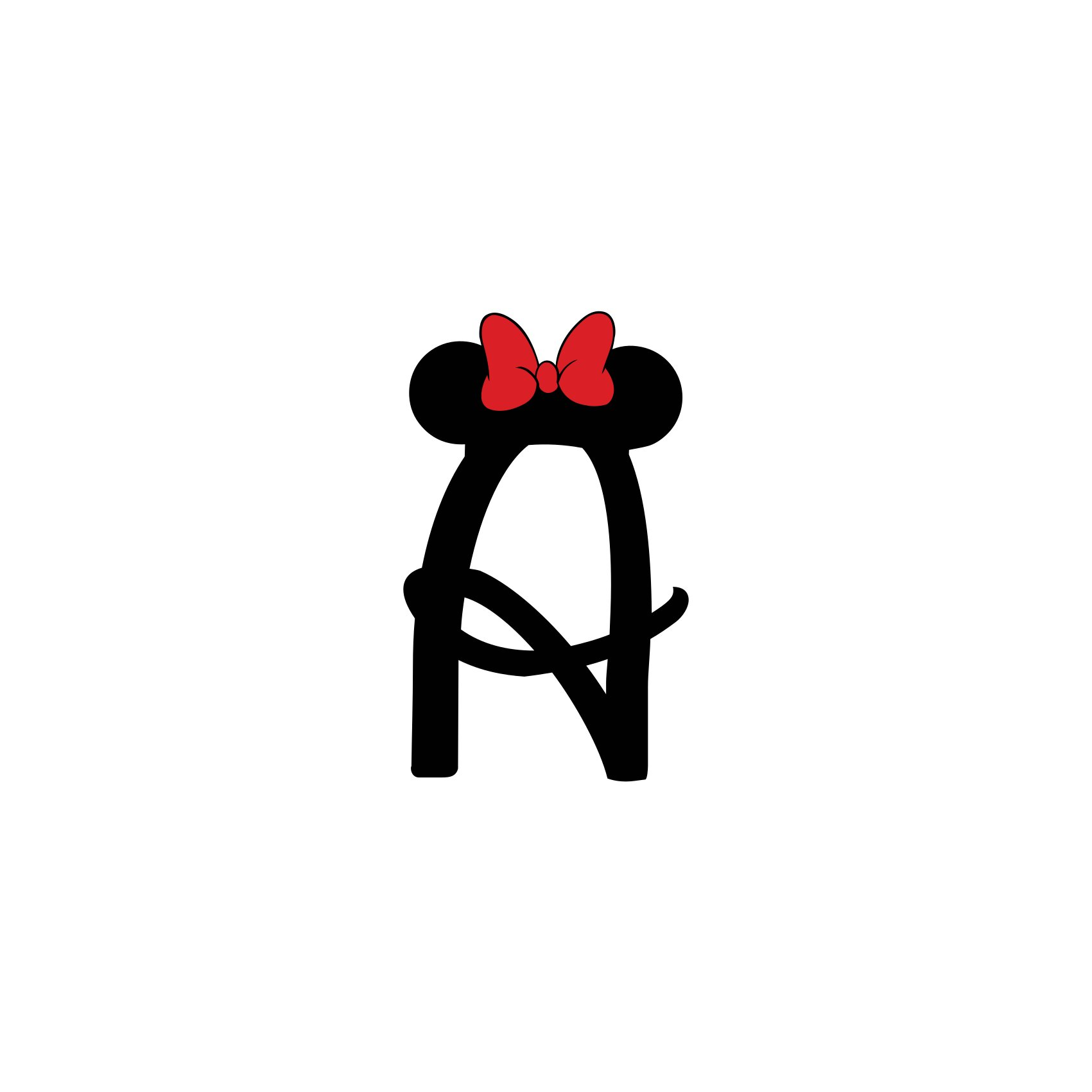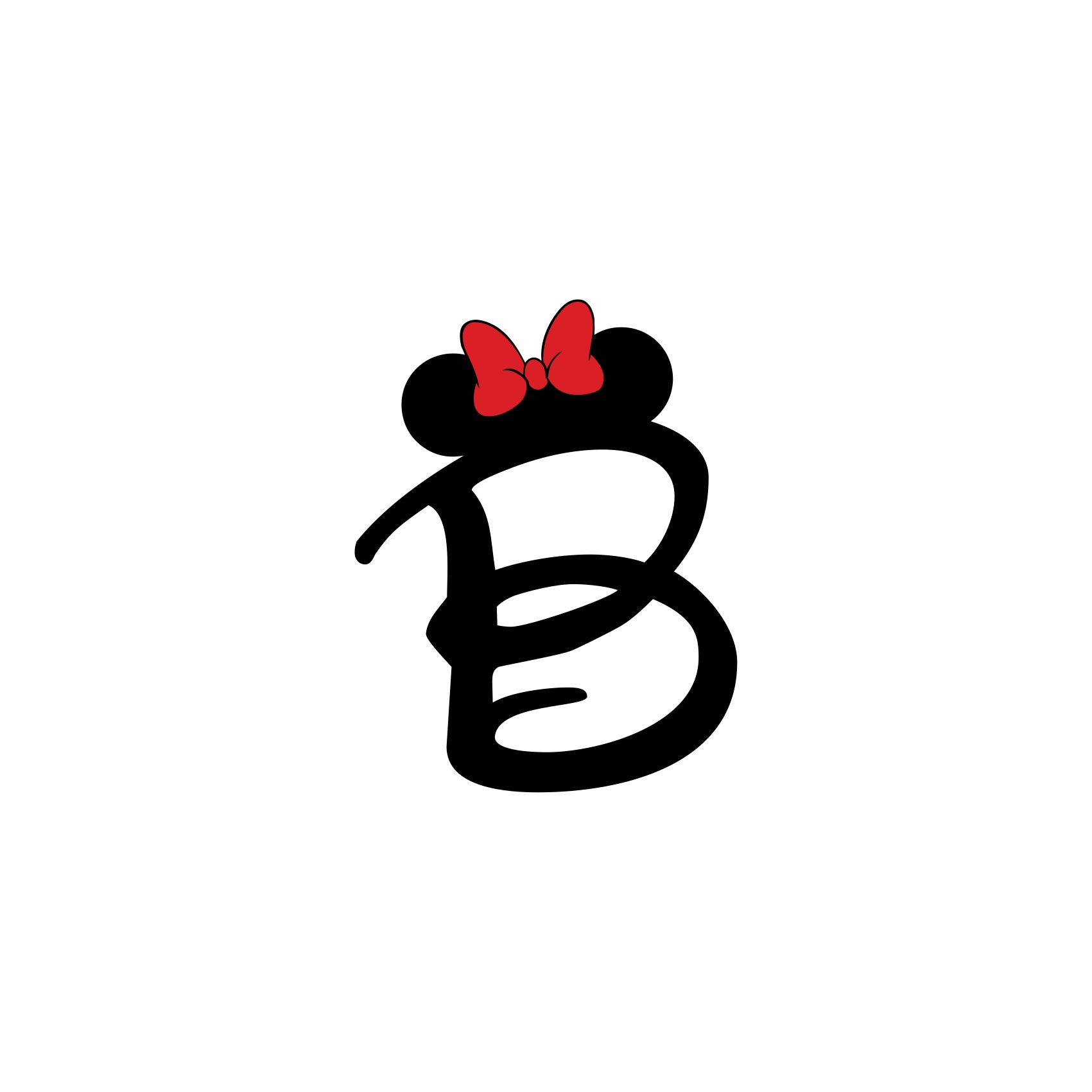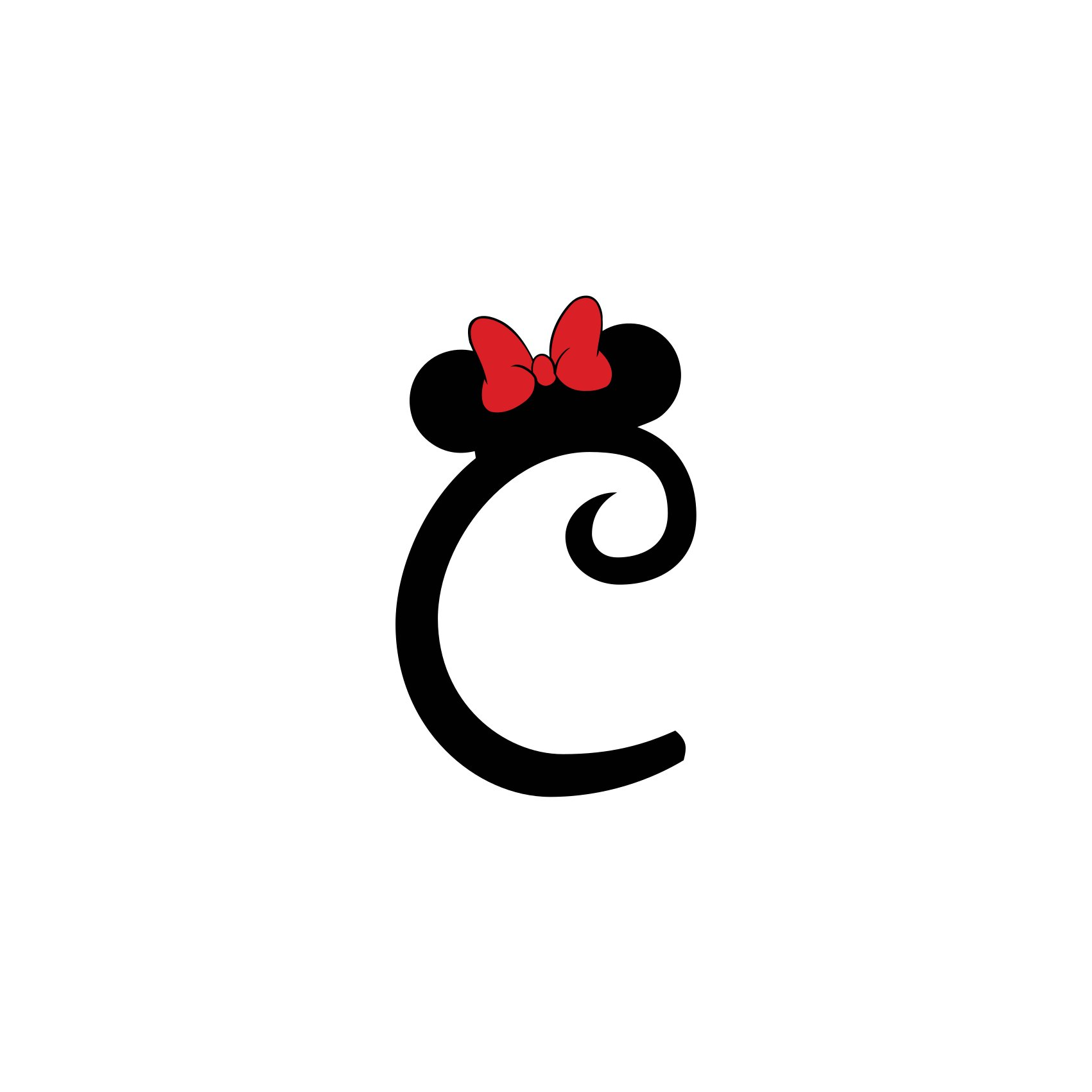
Cute Magic Bow Monogramm Schriftart – Verspieltes Bastel-Alphabet | Cricut-kompatibel
• Die Cute Magic Bow Monogramm Schriftart ist ein verspieltes dekoratives Alphabet, inspiriert von niedlichen, handgezeichnet wirkenden Schriftstilen. Jeder Grossbuchstabe besitzt eine runde, weiche Form und wird durch eine kleine Schleife ergänzt, die den Buchstaben eine fröhliche und charmante Ausstrahlung verleiht. Die Formen sind leicht unregelmässig gestaltet, um eine freundliche, handgemachte Optik zu erzeugen, bleiben jedoch klar und gut erkennbar – ideal für Schneideprojekte.
• Die Schrift enthält Grossbuchstaben von A–Z und eignet sich damit für viele einfache Personalisierungsprojekte. Durch den einheitlichen Stil wirken Namen, Wörter und kurze Texte harmonisch und optisch ausgewogen.
• Diese Monogramm-Schrift passt besonders gut zu kreativen Bastelprojekten mit einem verspielten oder kindgerechten Stil. Sie eignet sich beispielsweise für Dekorationen, personalisierte Geschenke oder thematische Designs. Die kräftigen Rundungen und klaren Konturen machen die Buchstaben gut geeignet für Schneideanwendungen mit Vinyl, Papier oder anderen Bastelmaterialien.